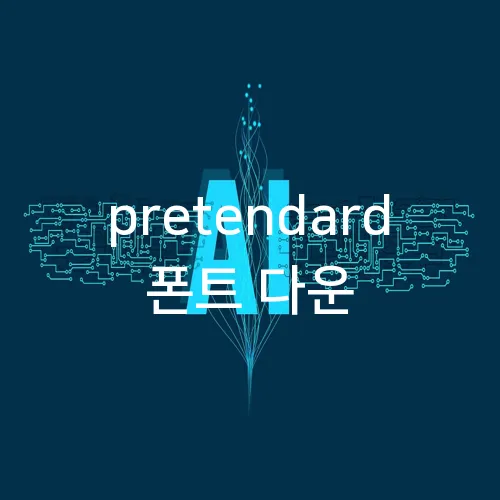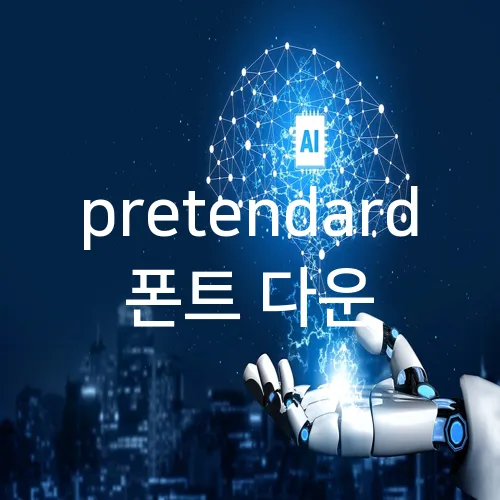
Pretendard 폰트를 다운로드하기 위해 가장 안전한 방법은 공식 웹사이트에서 직접 받는 것입니다. Pretendard는 서체 디자이너인 ‘Jungmin Hong’이 개발한 오픈소스 서체로, 웹과 모바일 환경에서 깔끔하고 읽기 쉽게 사용할 수 있습니다. 공식 웹사이트를 통해 최신 버전의 Pretendard 폰트를 쉽게 다운로드할 수 있습니다.
Pretendard 폰트는 다양한 굵기와 스타일을 제공하여 디자인 작업에 적합합니다. 특정 응용 프로그램에서 폰트가 제대로 표시되지 않을 경우, 업데이트가 필요한지 확인하거나 폰트 관리자에서 다시 활성화해 보세요. 또한, 고해상도 화면에서는 Pretendard가 더 선명하게 보이므로 이러한 환경에서 작업 시 이점을 누릴 수 있습니다.
5. Pretendard 폰트와 함께 사용하는 추천 폰트 조합
Pretendard 폰트와 잘 어울리는 추천 폰트 조합
Pretendard 폰트를 다운받아 사용하시면서, 다양한 프로젝트에 적합한 폰트 조합을 찾고 계신가요? Pretendard는 모던하고 깔끔한 디자인으로, 특히 웹과 모바일 환경에서 읽기 쉬운 가독성을 제공합니다. 이는 다양한 폰트와의 조합에서도 훌륭한 성과를 보여줍니다.
– Noto Sans: Google에서 개발한 Noto Sans는 Pretendard와 비슷한 세련된 느낌을 줍니다. Noto Sans는 다양한 언어를 지원하며, Pretendard의 직선적인 느낌과 잘 어울립니다.
– Roboto: Roboto는 Google의 대표적인 서체 중 하나로, 미니멀리즘과 현대적인 디자인 요소를 강조하고 있습니다. Pretendard와 조합하면, 차분하면서도 프로페셔널한 느낌을 낼 수 있습니다.
– Montserrat: Montserrat는 대문자와 숫자가 돋보이는 스타일로, 헤드라인에 사용하기 적합합니다. Pretendard의 본문과 Montserrat의 헤드라인 조합은 확실한 시각적 대비를 제공합니다.
– Merriweather: 조금 더 전통적인 서체를 원하신다면, Merriweather를 고려해 보세요. 이 고전적인 세리프 폰트는 Pretendard와 함께 사용 시 더욱 깊이 있는 텍스트 구성을 완성할 수 있습니다.
– Lato: Lato는 부드러운 곡선미와 넓은 글자 여백이 특징입니다. 이는 Pretendard의 직선적인 폰트와 잘 어우러져, 친근한 디자인을 연출할 수 있습니다.
Pretendard 폰트 활용 팁
– 웹사이트에서는 가독성을 위해 적절한 크기와 라인 간격 설정
– 인쇄물에서는 폰트 무게와 스타일 조합으로 다양한 표현 가능
Pretendard의 다양한 스타일은 명함, 포스터, 웹페이지 등에 적합합니다. 이를 통해 다양한 디자인 요구사항을 충족할 수 있습니다.
Pretendard 폰트는 현대적이고 깨끗한 느낌을 제공합니다. 사용자 편의를 위한 다양한 방법으로의 다운로드와 세련된 디자인은 많은 디자이너에게 필수적인 요소로 자리잡고 있습니다.